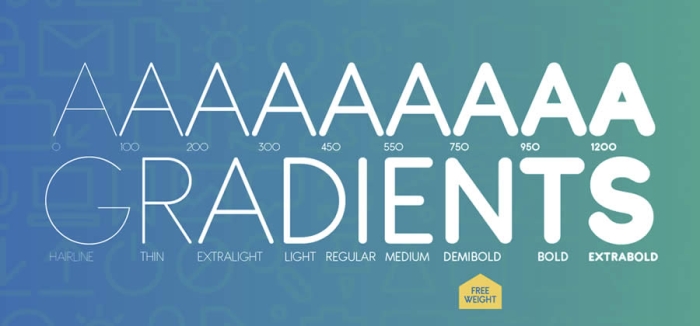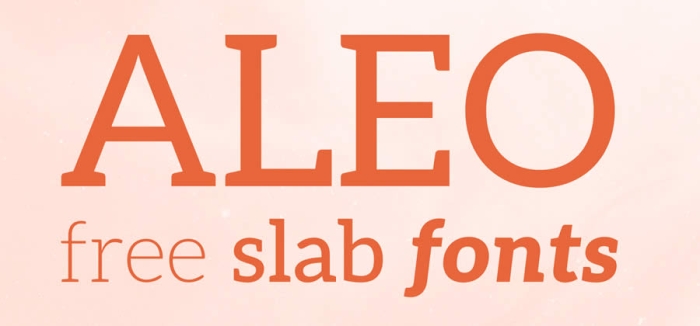
Stai cercando di aggiungere un tocco di coraggio ai tuoi progetti di design? Non cercare oltre I font heavy ultra bold sono il modo perfetto per attirare l’attenzione e lasciare un’impressione duratura. La buona notizia è che non devi rompere la banca per accedere a questi font potenti. Abbiamo curato una lista dei migliori font heavy ultra bold gratuiti disponibili online.
Dai sans-serif moderni ai font script drammatici, la nostra selezione ha qualcosa per ogni stile di design. Sia che tu stia creando un logo, un poster o un sito web, questi font sono sicuri di far risaltare il tuo messaggio. Con le loro linee spesse e apparenza impressionante, sono perfetti per titoli, intestazioni e testo di enfasi.
Le nostre scelte migliori includono font come Montserrat Ultra Bold, Great Vibes e Bebas Neue. Ogni font è stato scelto con cura per il suo carattere unico e versatilità. Sia che tu sia un designer professionista o un appassionato di DIY, questi font sono facili da usare e innalzeranno il tuo gioco di design.